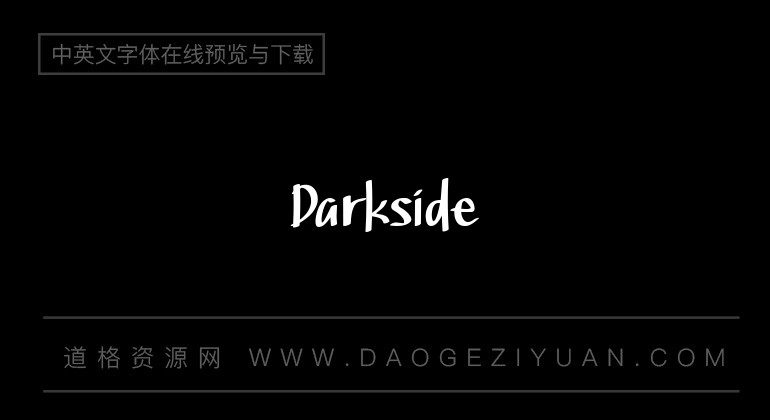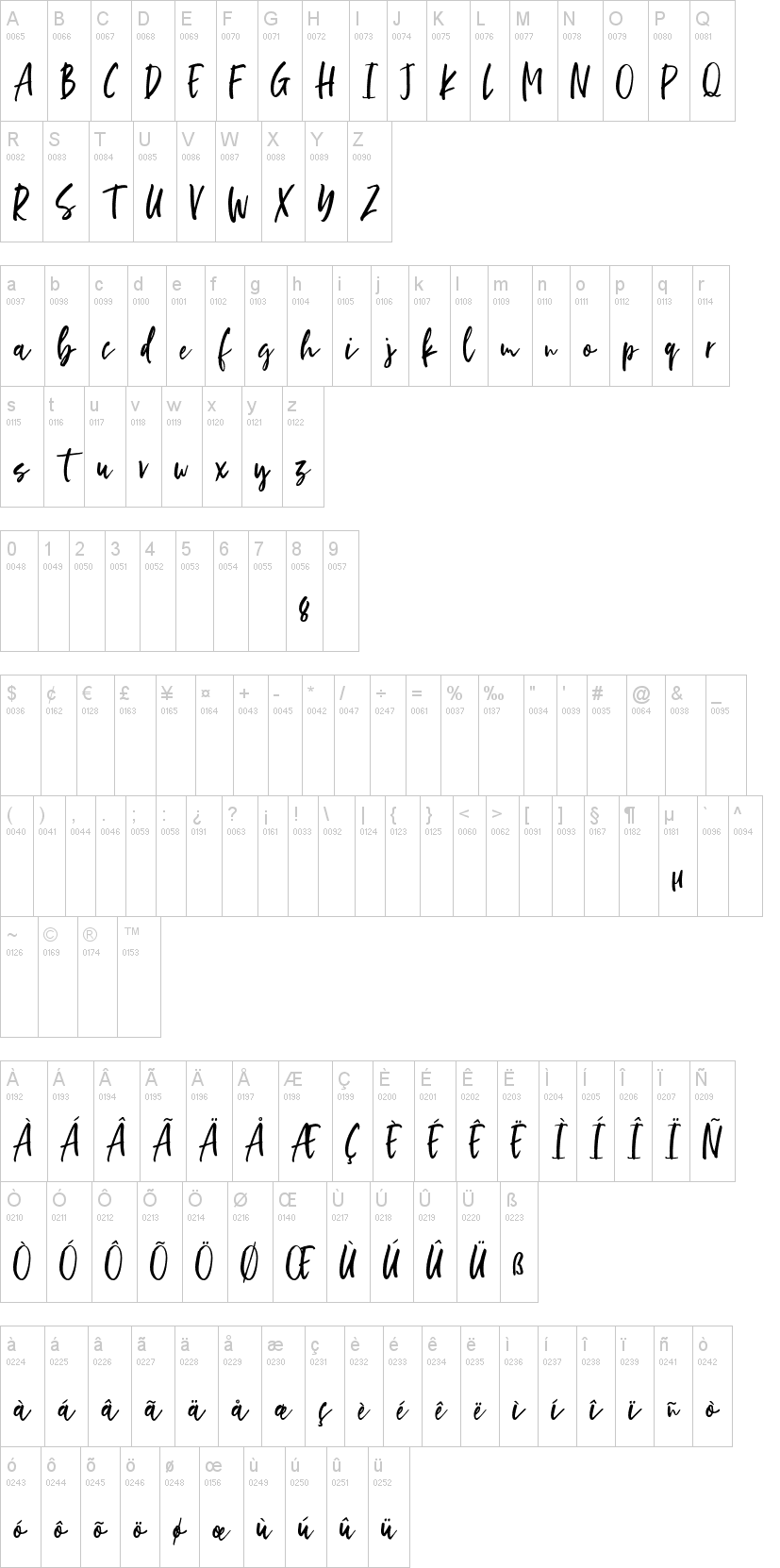
Darkside
Darkside 是一种免费的手写风格字体,由 Jérémie Dupuis 设计。这个字体的设计灵感来源于黑暗的幻想世界和古老的书信,字形流畅而且具有艺术感。Darkside 字体的特点是其笔画的不规则和厚度变化,这使得每一个字母都有个性和魅力。它适合于各种设计项目,如海报、标志、书籍封面、名片等。Darkside 字体提供了常规和粗体两种字重,可以用于多种场合,不同字重的组合可以创造出更加有趣的效果。
Darkside是一款非常不错的手写艺术字体,具有很好的视觉感,适合于文化类的宣传设计、商业类品牌的广告和产品包装设计以及个性化文字排版等较多场景。
Darkside字符映射图